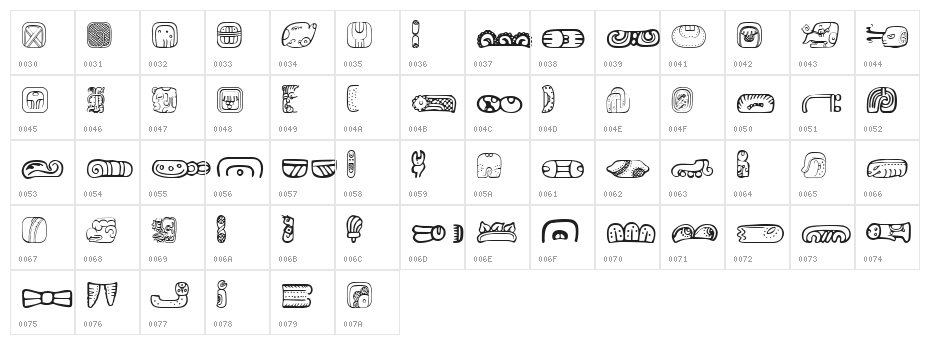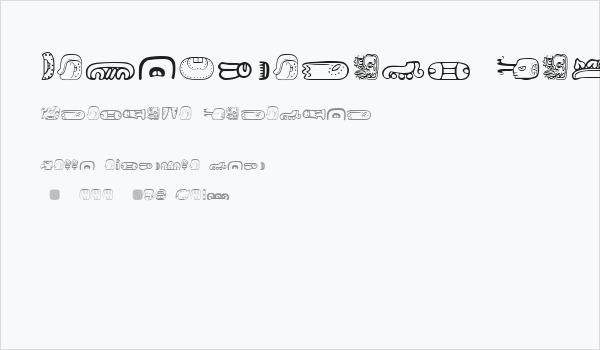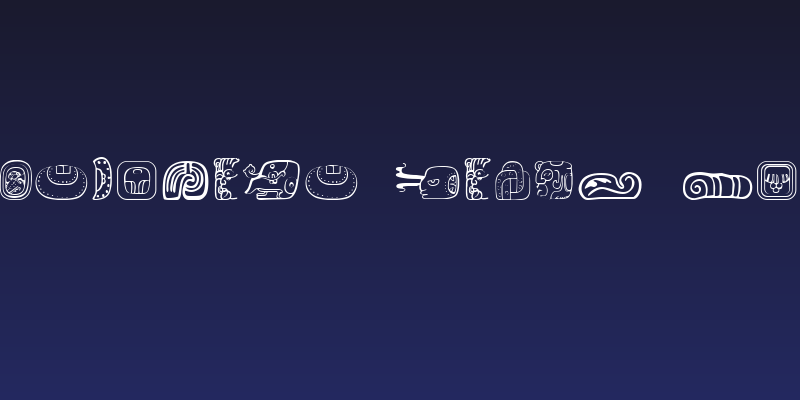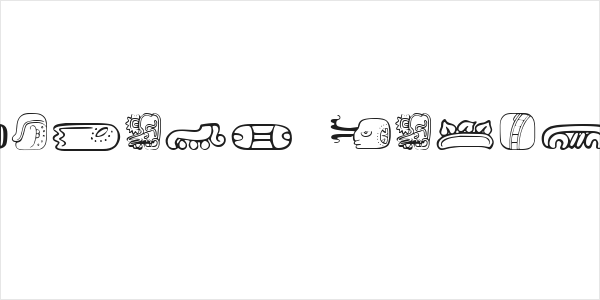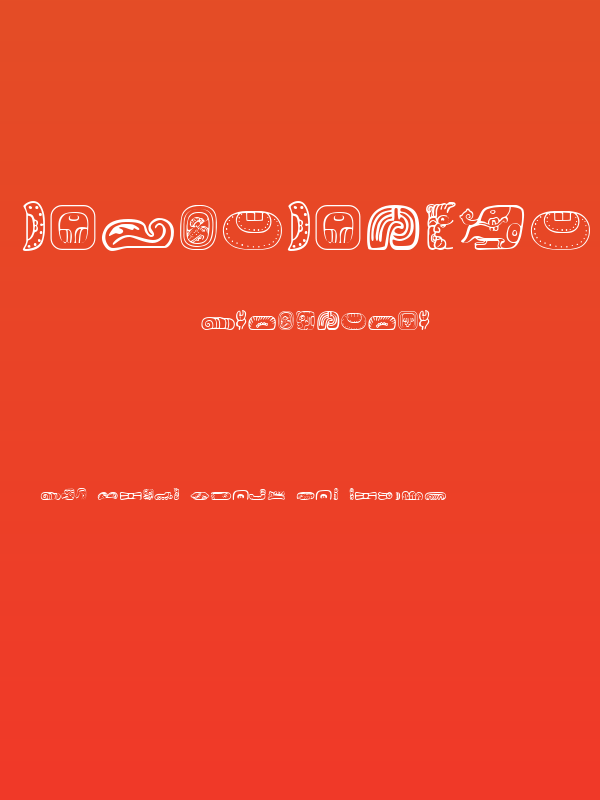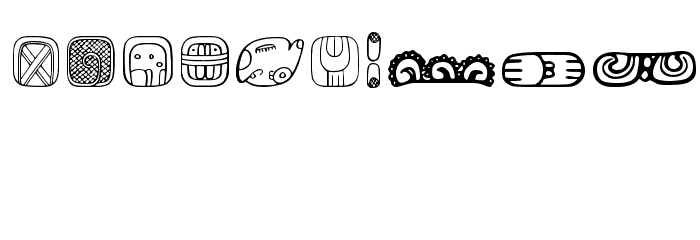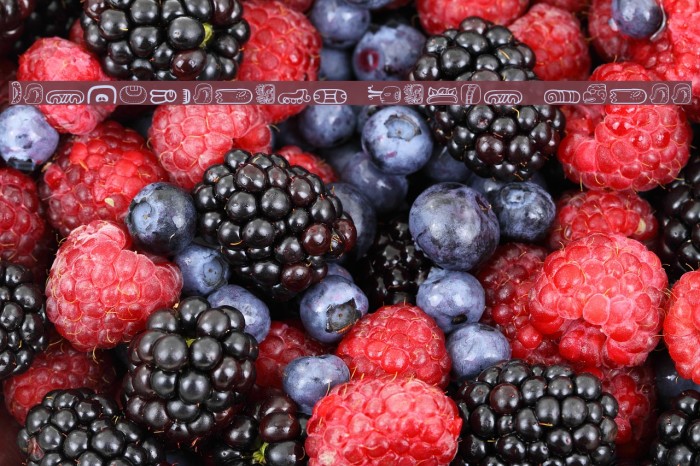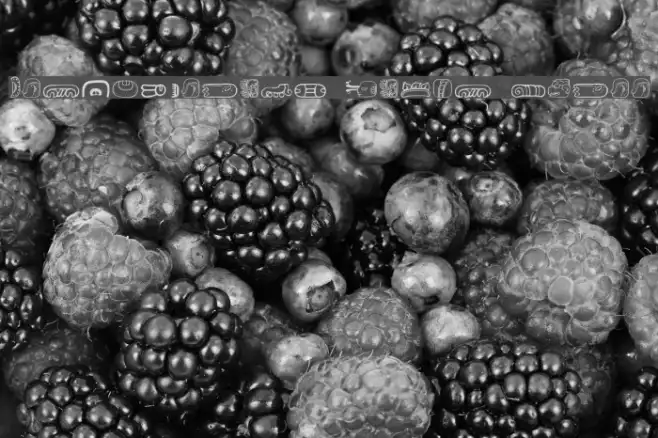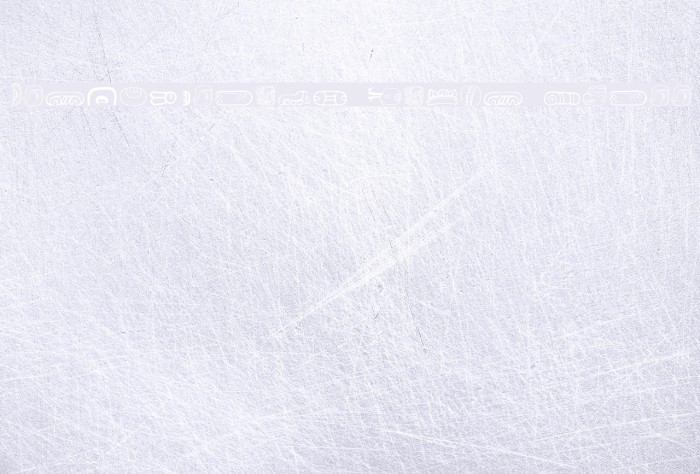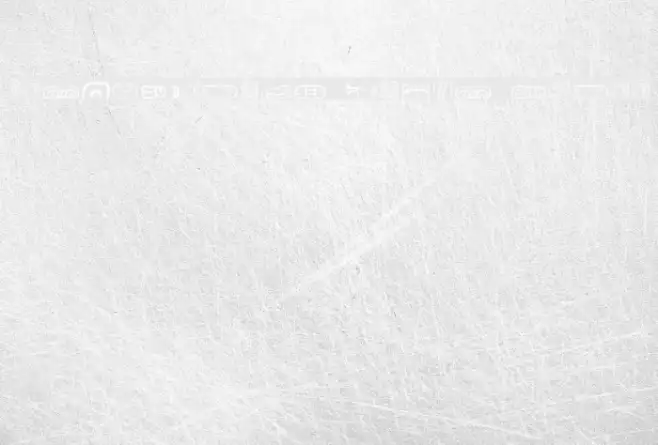
MesoAmerica Dings Three Font
| Caso d'uso | Logos, Themed artwork, Educational materials |
| Progetti proposti | Ideal for cultural exhibitions, historical documentaries, themed artwork, educational materials on ancient civilizations, and decorative projects requiring a historical touch. |